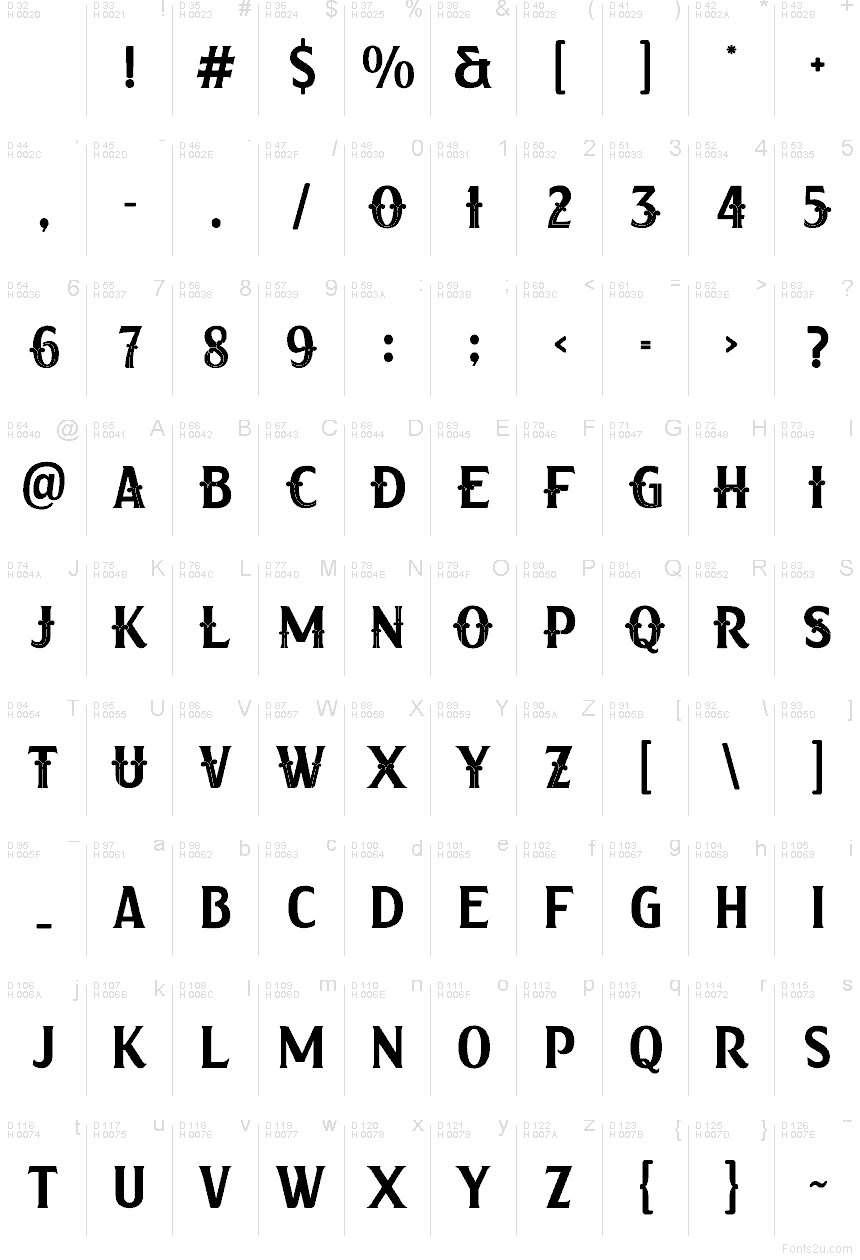
Catalunya Flower de Trequartista Studio es una tipografía display gratuita de letras mayúsculas con motivos florales que posee el equilibrio de una serif romana clásica con un toque botánico. Sus letras se sienten elegantes y de alto contraste, mientras que la C inicial introduce el concepto con un detalle de doble tallo rizado que se lee más como un ornamento que como un simple adorno.
Es ideal para etiquetas de vino, empaques boutique, títulos de pósteres, portadas de libros y branding de restaurantes donde una silueta formal necesita un matiz más delicado. Como tipografía gratuita, también funciona bien en titulares cortos, monogramas y tarjetas de presentación, ya que esos remates anchos y esa curva floral dan, incluso a pocas letras, un tono elegante y ceremonial.
Catalunya Flower de Trequartista Studio es una tipografía display romana (solo mayúsculas).